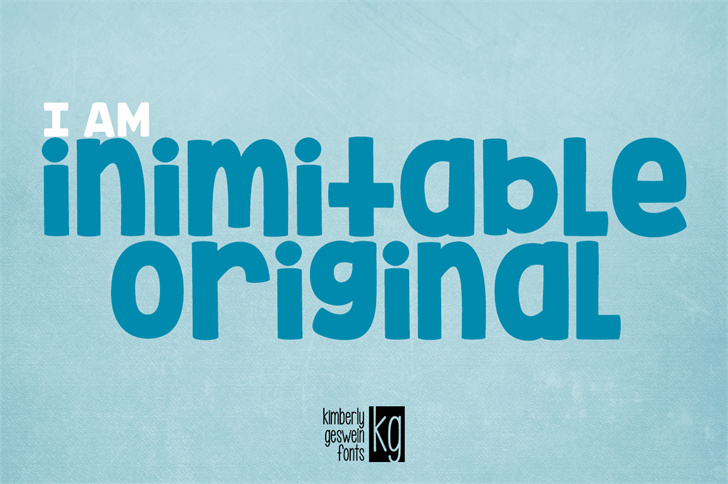
KG Inimitable Original Font – Download Grátis
Na categoria de Playful Fonts, a fonte KG Inimitable Original é uma escolha perfeita para quem deseja dar um toque único à sua próxima criação digital. Desenvolvida por Kimberly Geswein, essa fonte oferece um estilo casual e versátil que se destaca entre as muitas opções disponíveis. Com linhas levemente espessadas e interessantes detalhes, a KG Inimitable Original atende perfeitamente às necessidades de projetos como cartazes, logos ou editoriais para o seu site. Suas formas curvilíneas e características distintivas tornam-a uma escolha ideal para quem busca um visual criativo que destaque suas criações. Seja você designer de interiores, criador de blogs pessoais ou até mesmo um profissional da web, a fonte KG Inimitable Original pode ser o componente crucial para finalizar seu projeto. Combinada com cores vibrantes e imagens impactantes, essa fonte trará vida ao seu design. Para acessar todas as funcionalidades desta incrível fonte, visite o site de Kimberly Geswein, que oferece uma licença comercial. Aqui está um exemplo de como incorporar esta fonte em seus trabalhos: “Com a nossa fonte KG Inimitable Original, você pode dar ao seu design um toque único e chamativo.”
Designer: Kimberly Geswein